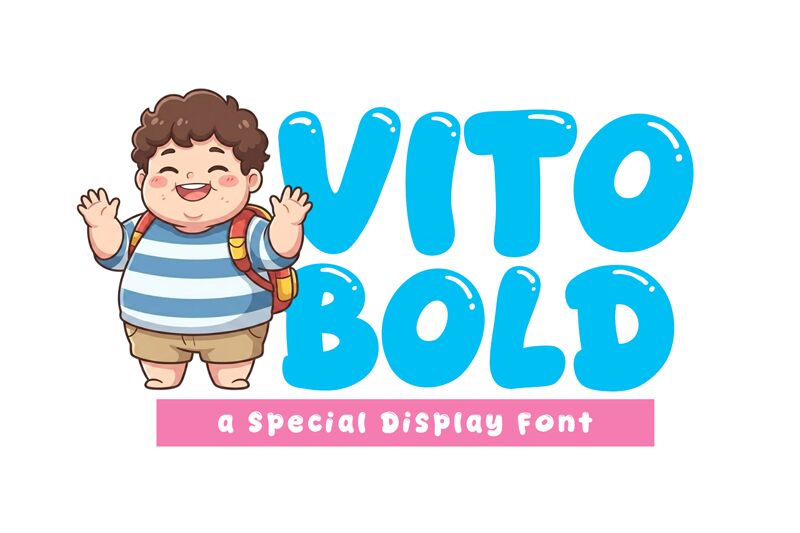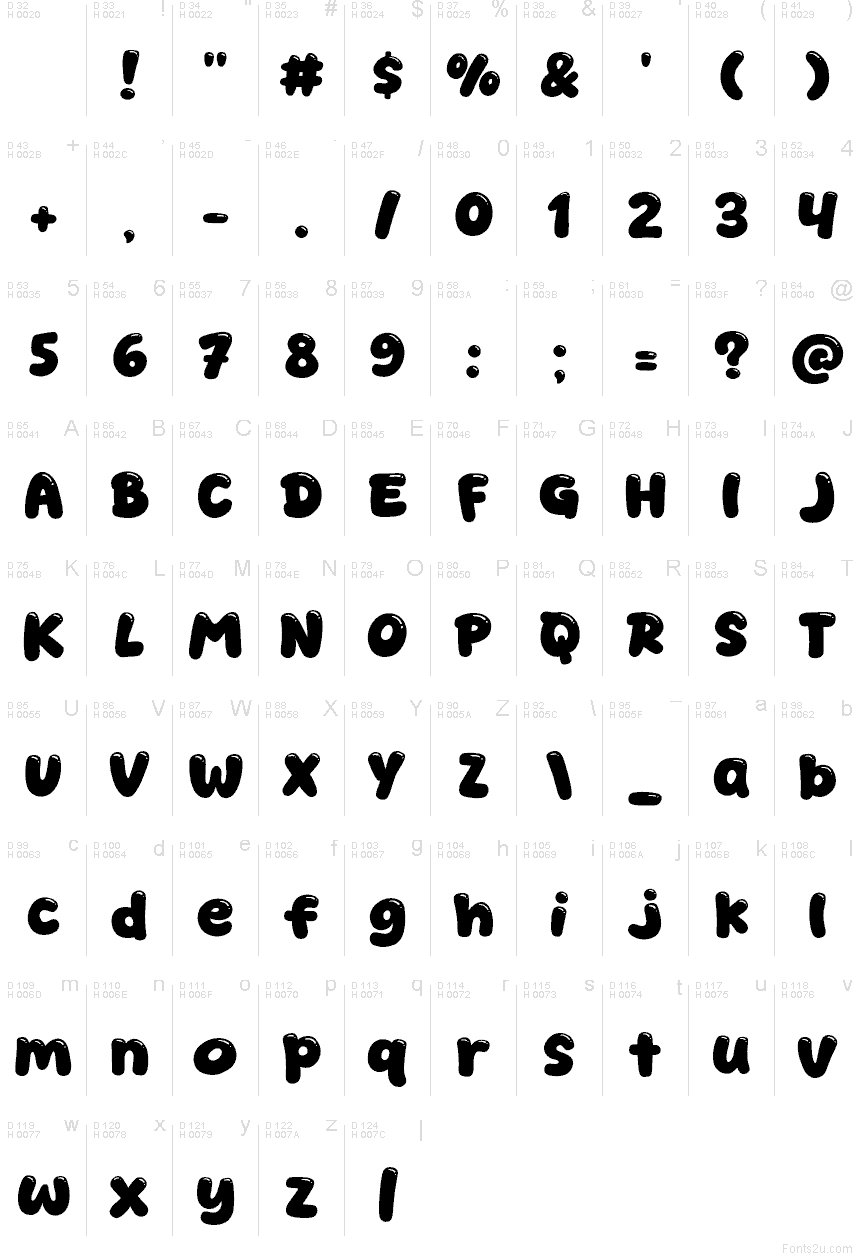
Vito Bold autorstwa Khurasan & Jalembe to bezpłatny, kreskówkowy font z dużymi literami przypominającymi bąbelki oraz miękkim, napompowanym wyglądem. Formy są masywne i zabawne, z zaokrąglonymi krawędziami, wyrazistymi sylwetkami i błyszczącymi detalami, co sprawia, że krój ten bardziej kojarzy się z opakowaniami zabawek czy grafiką komiksową niż z czymkolwiek formalnym.
Naturalnie pasuje do plakatów dla dzieci, opakowań przekąsek, okładek komiksów, zaproszeń czy miniaturek na YouTube, gdzie krótkie słowa mogą wykorzystać jego puszysty rytm i radosną wagę. Jako bezpłatny font świetnie sprawdza się w żartobliwych logotypach i przyciągających wzrok nagłówkach, zwłaszcza gdy zależy Ci na tym, aby litery wyglądały przyjaźnie, dynamicznie i były nieco przerysowane.